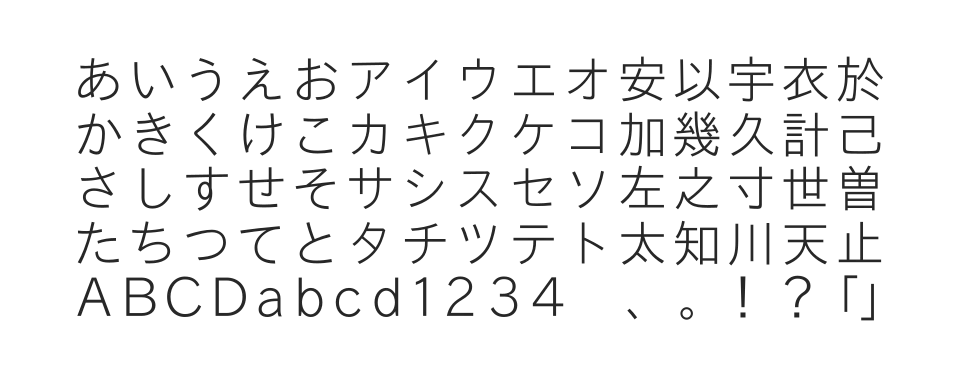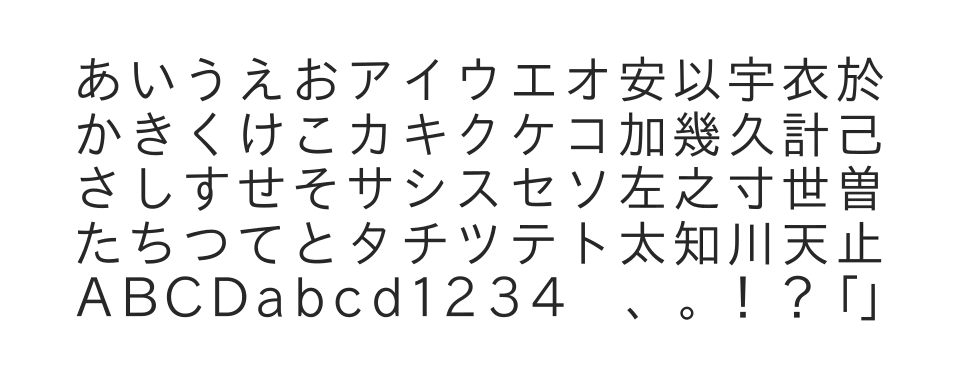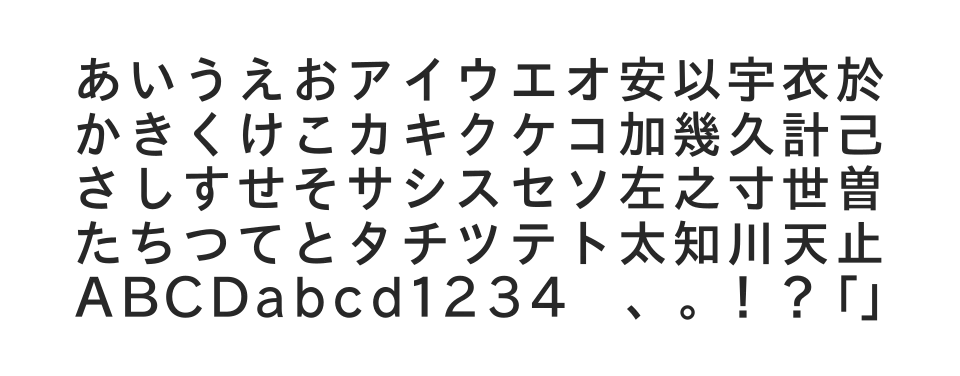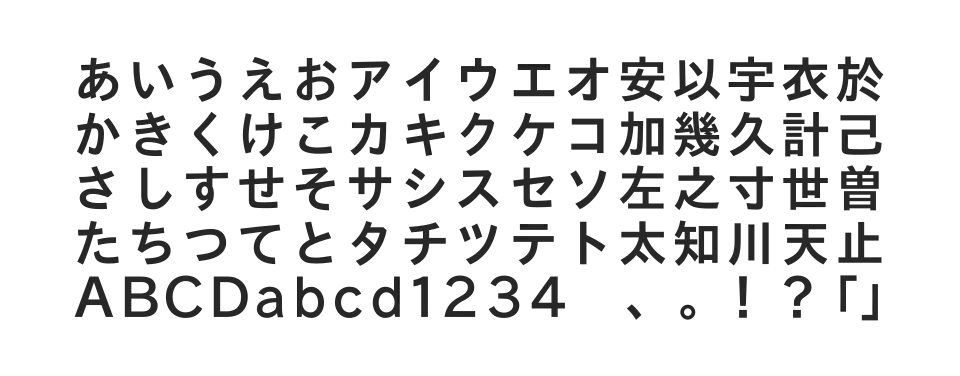
飾り気のないシンプルなエレメントで、極端に角張った字形を避けた読みやすいゴシック体。自然の呼吸を静かに感じさせながらも力強い印象を与えるボールドウェイト。
飾り気のないシンプルなエレメントで、極端に角張った字形を避けた読みやすいゴシック体。穏やかな表情を保ちながらもしっかりとした存在感を持つデミボールドウェイト。
飾り気のないシンプルなエレメントで、極端に角張った字形を避けた読みやすいゴシック体。小さく印字してもヌケがよく、大きく印字しても黒味や形にムラがないライトウェイト。
飾り気のないシンプルなエレメントで、極端に角張った字形を避けた読みやすいゴシック体。それぞれのウエイトに合わせて文字の大きさと明るさを決定したレギュラーウェイト。
飾り気のないシンプルなエレメントで、極端に角張った字形を避けた読みやすいゴシック体。自然の呼吸を静かに感じさせる穏やかな表情を保つスーパーライトウェイト。